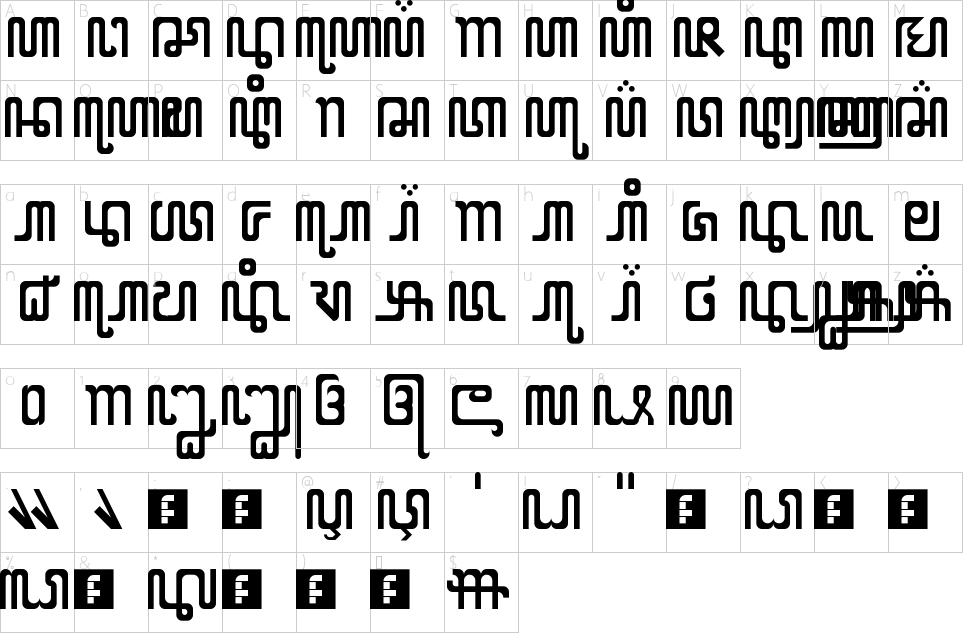
X Code From East Font
Descubra a elegância e a simplicidade da X Code From East, uma fonte exclusiva criada por Adien Gunarta. Inspirada em estilos de escrita orientais, esta fonte oferece uma fidelidade única aos traços tradicionais da cultura asiática. A X Code From East não apenas traz um novo nível de profissionalismo a qualquer projeto de design, mas também uma conexão vibrante com a rica herança cultural do Oriente. Com seu design cuidadosamente elaborado, a X Code From East é uma escolha ideal para designers que desejam incorporar um toque de elegância e versatilidade em suas criações digitais. Este design de fonte gratuita é perfeito tanto para desenvolvedores de código quanto para qualquer designer que busca complementar seus projetos com um toque oriental. Com apenas um clique, você pode instalar e experimentar as inúmeras possibilidades da X Code From East, garantindo que suas criações se destaquem entre o pacote de recursos gráficos disponíveis gratuitamente.